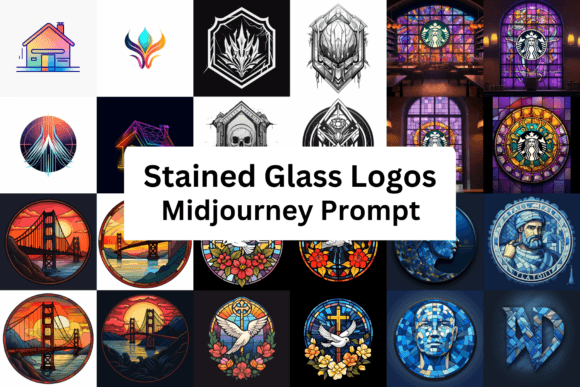
Stained Glass Logos
Trouver les bons éléments de conception peut être un défi, mais Stained Glass Logos propose une collection exceptionnelle qui rehausse instantanément votre travail.